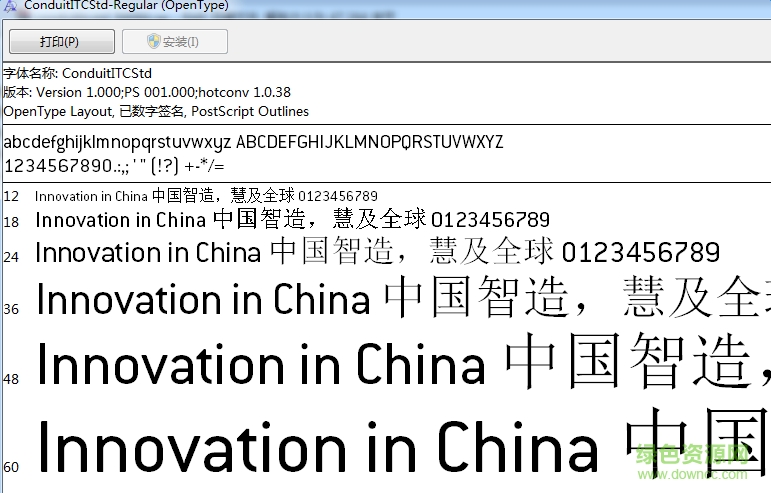
conduititcstd字體是一款英文字體庫(kù)中的個(gè)性字體,該字體可廣泛應(yīng)用于平面設(shè)計(jì)、廣告設(shè)計(jì)、報(bào)紙雜志、正文標(biāo)題等領(lǐng)域,喜歡的網(wǎng)友可免費(fèi)下載收藏。
conduititcstd字體是英文字體庫(kù)中極具個(gè)性的一款字體,該字體的字體端莊大氣,自行整體線條非常纖細(xì),讓用戶有一種舒適的感覺。有喜歡的朋友趕快來綠色資源網(wǎng)下載使用吧!